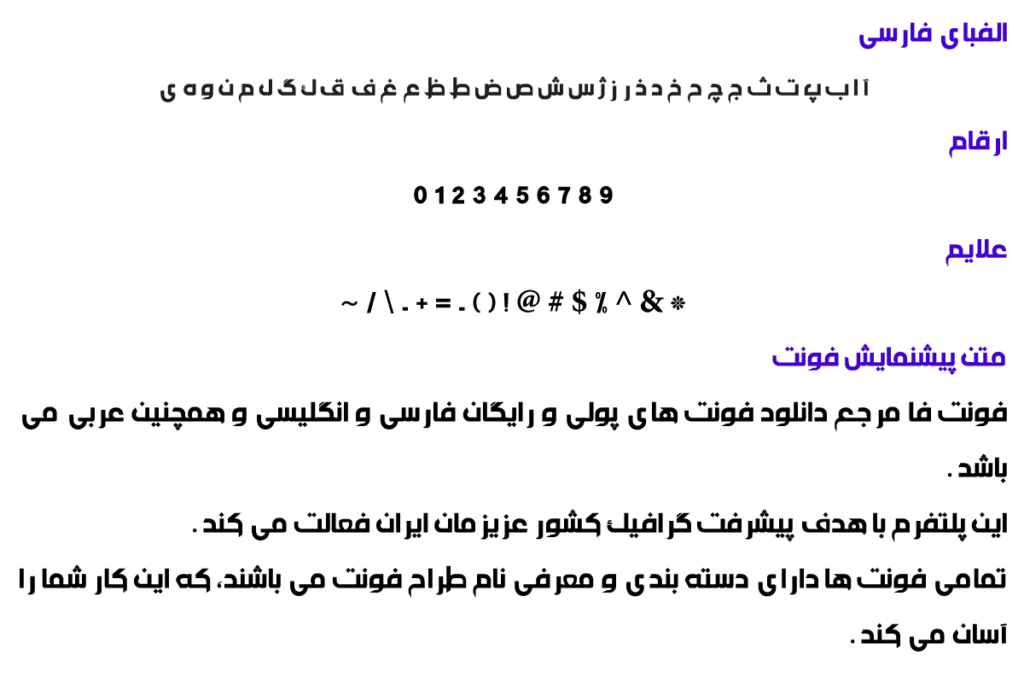
فونت فارسی امینه – A Amine
طراح فونت: علی سواری نوع فونت: فونت هندسی
پیشنمایش فونت امینه
توضیحات و معرفی فونت امینه
فونت فارسی امینه ( A Amine ) از مجموعه فونت های آزاد می باشد، و نیز نوع فونت هندسی می باشد.
فونت خوشگل مربوط توسط علی سواری طراحی و ساخته شده است.
در تصویر زیر میتوانید شعر زیبای وطن که با این تایپ فیس زیبا طراحی شده است ببینید.